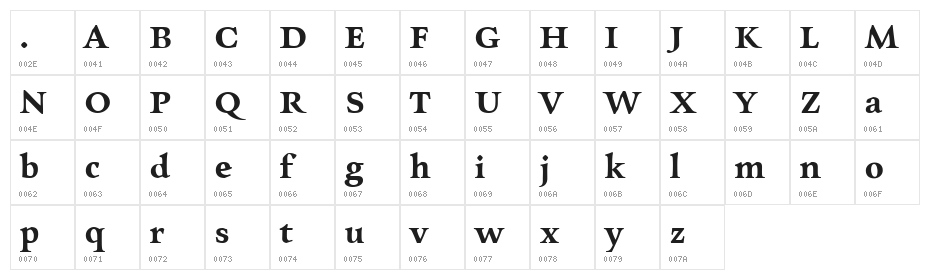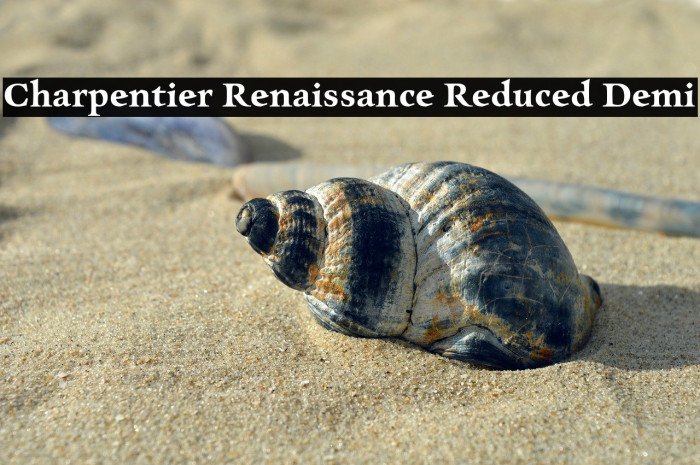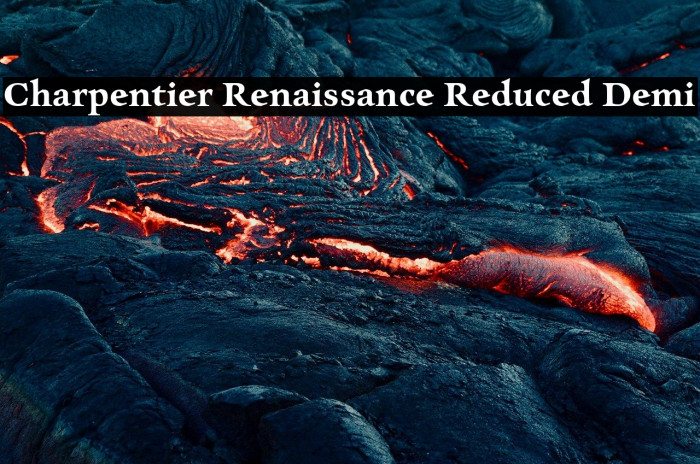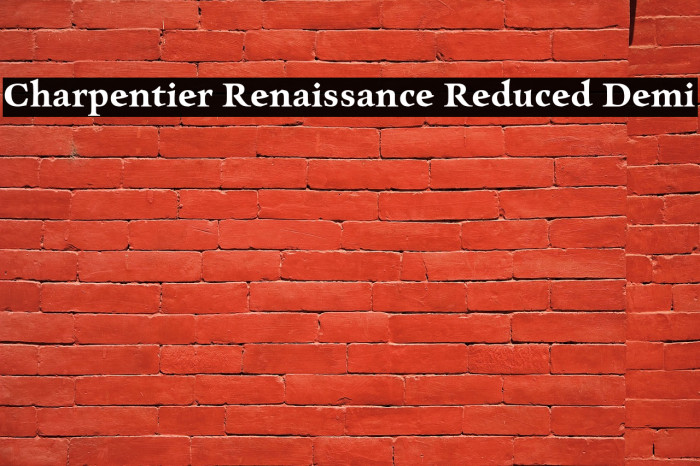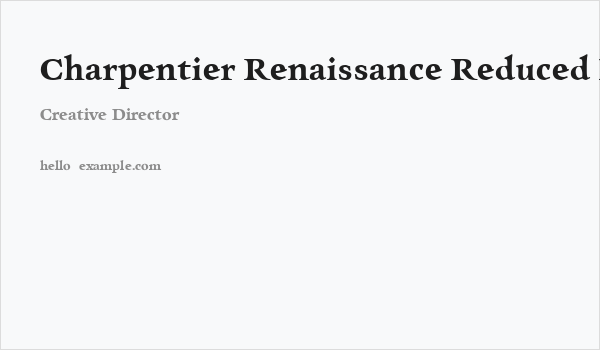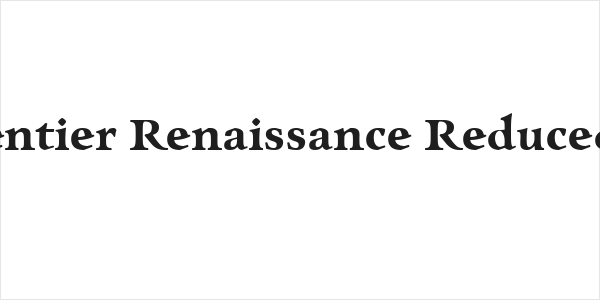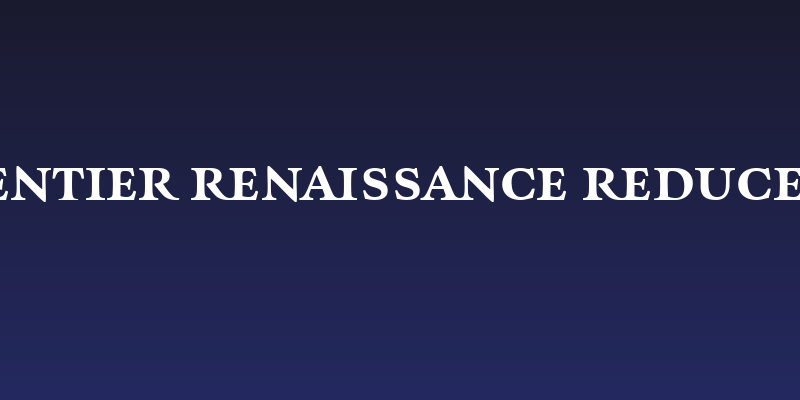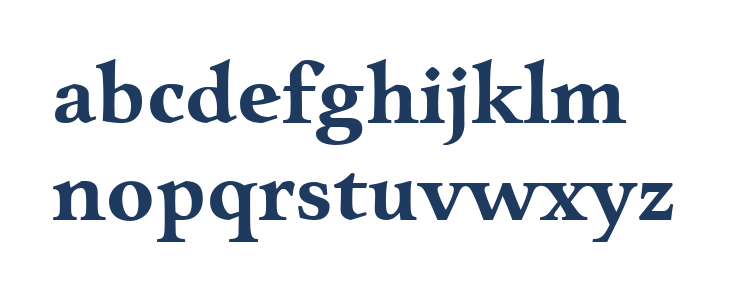
Charpentier Renaissance Reduced Demi Font
| 整体风格 | Classic |
| 使用场景 | Headlines, Logos, Formal documents |
| 推荐项目 | Ideal for use in formal invitations, historical publications, book covers, and branding that requires a touch of sophistication. |